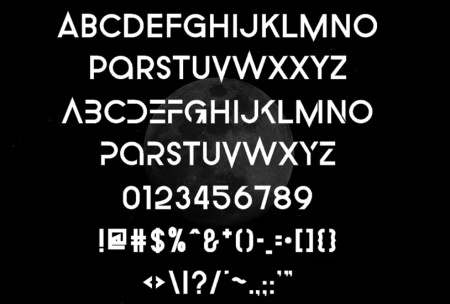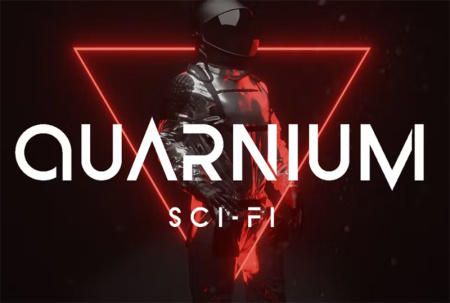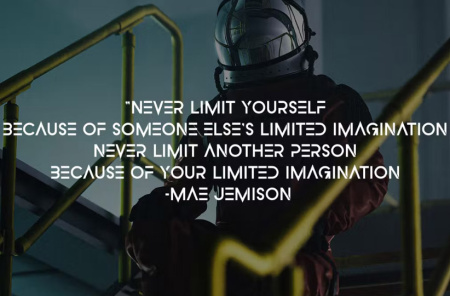
دانلود رایگان فونت ساده انگلیسی Starlynx
دانلود رایگان فونت انگلیسی ساده Starlynx
دانلود رایگان فونت ساده انگلیسی Starlynx از جی اف ایکس دانلود. یک فونت انگلیسی ساده و منحصر به فرد sans serif. بسیار مناسب برای شما که به یک تایپ فیس برای طراحی لوگو، مجله، رسانه های اجتماعی، بروشور و بسیاری موارد دیگر نیاز دارید.
✅ نام فونت: Starlynx
✅ حروف بزرگ
✅ حروف کوچک
✅ نقطه گذاری
✅ اعداد